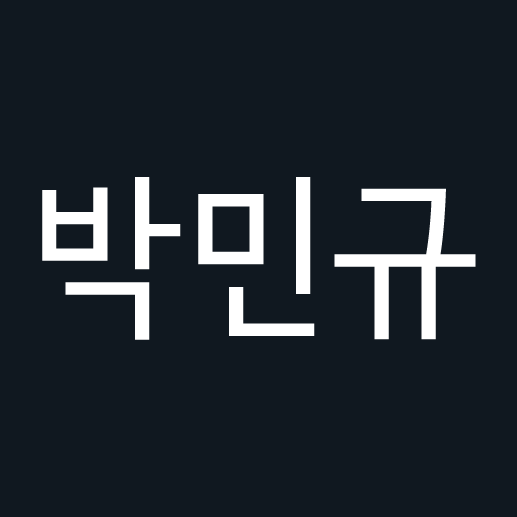
박민규체의 뼈대를 기반으로 그려져 구조와 비율을 공유하지만 획의 표현은 곡선과 꺾임을 사용해 휴머니스트 세리프의 인상을 보입니다. 8-11 포인트 크기의 글자에 최적화 되었고, 첫 닿자의 위치가 글자의 윗 부분에 자리해 고른 글줄 흐름을 보입니다. 박민규체와 마찬가지로 닿자와 홀자가 작게 설계되었습니다.